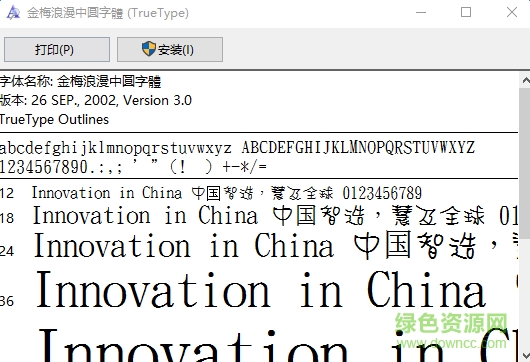
金梅浪漫中圓
金梅浪漫中圓字體是金梅字庫中的一款很有特色的字體,這款字體寫出來很好看,可以用于很多方面,比如書本印刷、廣告設(shè)計(jì)等都是很不錯(cuò)的,歡迎有需要的朋友來綠色資源網(wǎng)下載。
金梅浪漫中圓字體是一款很好看的字體,小編已經(jīng)為大家驗(yàn)證過了,寫出來的字確實(shí)不錯(cuò),大家快來下載吧。